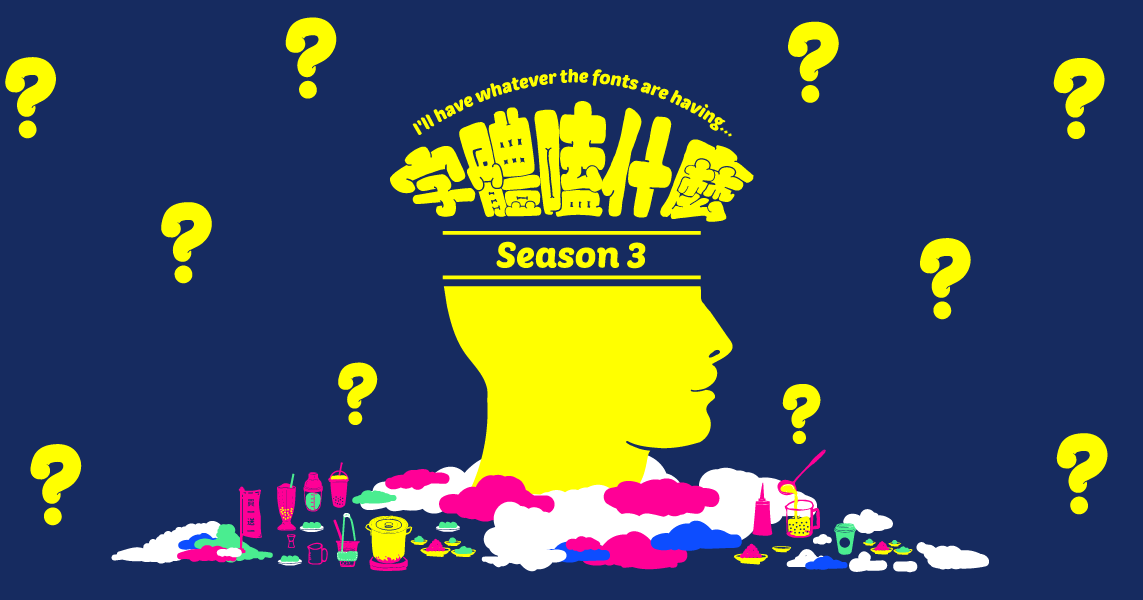
justfont 2019 年全新系列字體講座
🤯字體嗑什麼🤔
—Season 3—
字體嗑⋯⋯珍珠奶茶!
關於字體嗑什麼⋯⋯
根據研究,87%的人都不知道字體隨時都有意見,一見面就默默使喚你的大腦。手機、甜食、啤酒;報表、告示、簡報,都要參一腳。不論你靠什麼吃飯,它都要強勢刷存。這也未免太霸道了!
想到台灣,你會想到什麼?大概不得不提到「珍珠奶茶」這個國民飲品吧?脫胎自泡沫紅茶文化,經過數十年的發展,成為了紅遍兩岸三地(台灣、日本、美國,沒錯。)的台灣之光,絕對是國人的生存基本需求,沒有之一。但如果仔細想想,你嚐到的除了珍珠和奶茶之外,還有什麼呢?
嘴裡喝著珍奶的同時,眼睛所看到的,同時也操控你感官的,其實就是字體這個神秘元素。什麼樣的字體會刺激你的食慾和購買慾?甚至隨著時代的演變,手搖飲品的不同「訴求」,又是怎麼反映到他們使用的字體呢?珍珠奶茶你應該常常喝,那麼字體也更值得你和我們一起嚐嚐看!
- 字體與口感之間的連覺
- 手搖攤的字體風格演變
- 圓體和背後的設計故事
- 漢字與歐文的字體搭配
嘖嘖嘖,像字體這麼控制狂的小東西,千萬別對它一無所知,讓 justfont 說給你聽。不管字體嗑了什麼,都給我來一點!